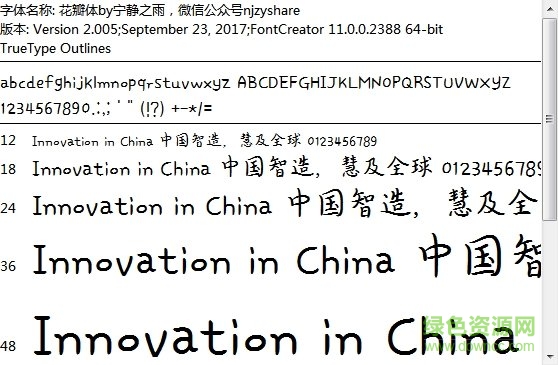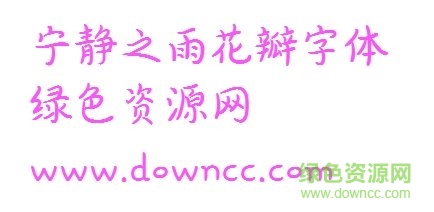
寧靜之雨花瓣字體
花瓣體是寧靜之雨美化后的一款藝術(shù)字體,筆觸更加柔和婉轉(zhuǎn),造型清晰而明麗,給人閱讀舒適怡然的視覺體驗(yàn),綠色資源網(wǎng)獨(dú)家推薦!
華為花瓣字體特色
流年的雨點(diǎn)打落的花瓣,是歲月飄零的記憶碎片,每一片都是一個(gè)曾經(jīng)過往的書簽。
寧靜之雨花瓣字體是美化后的卡通字體,取材于字體管家花瓣體,造型優(yōu)雅,極具美工特色,字跡較為深沉,適用于平面設(shè)計(jì)、包裝設(shè)計(jì)、印刷設(shè)計(jì)等場(chǎng)合。